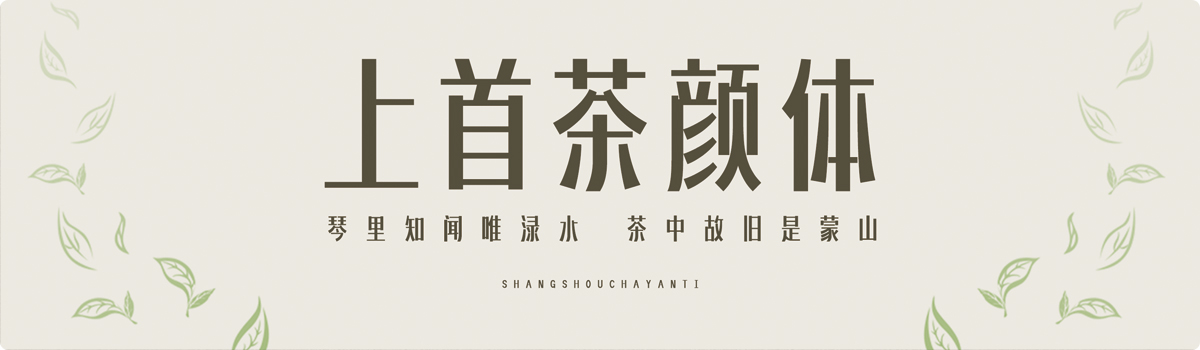
上首茶颜体
上首茶颜体,这款字体结构工整、笔画清晰,兼顾美观与易读性,适用于标题、正文、海报、包装、LOGO 等多种场景。字形优雅稳定,风格百搭耐看,适配日常排版与创意设计,让文字呈现更舒适、更具质感。上首茶颜体一笔一画,皆是细节,以均衡的比例、流畅的线条打造舒适视觉体验,字形端正大气,风格简约现代。无论是商业设计、品牌宣传还是日常排版,都能轻松驾驭,让文字更有格调与力量。上首茶颜体字体下载。